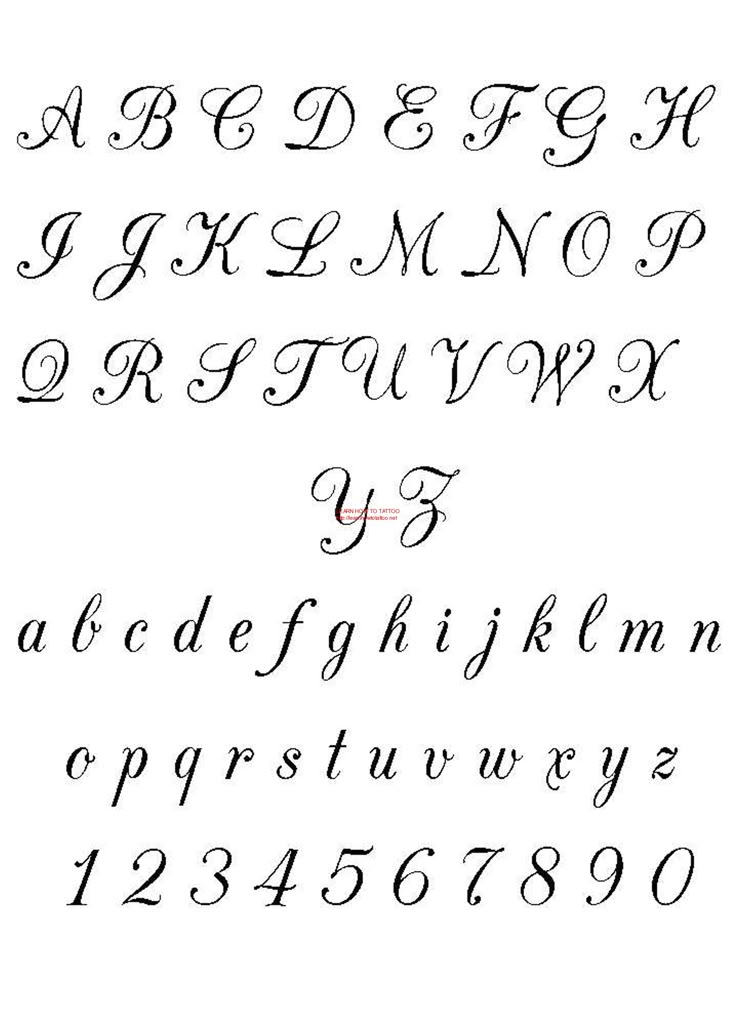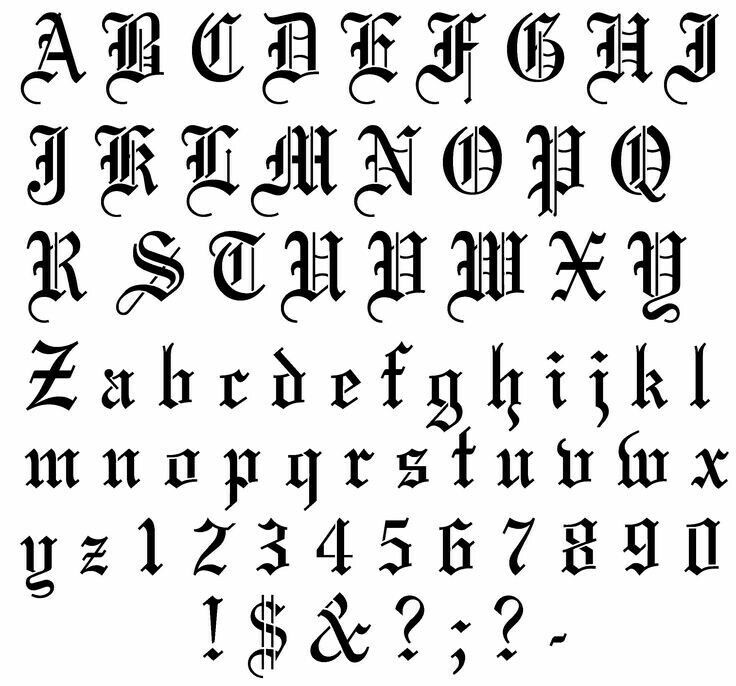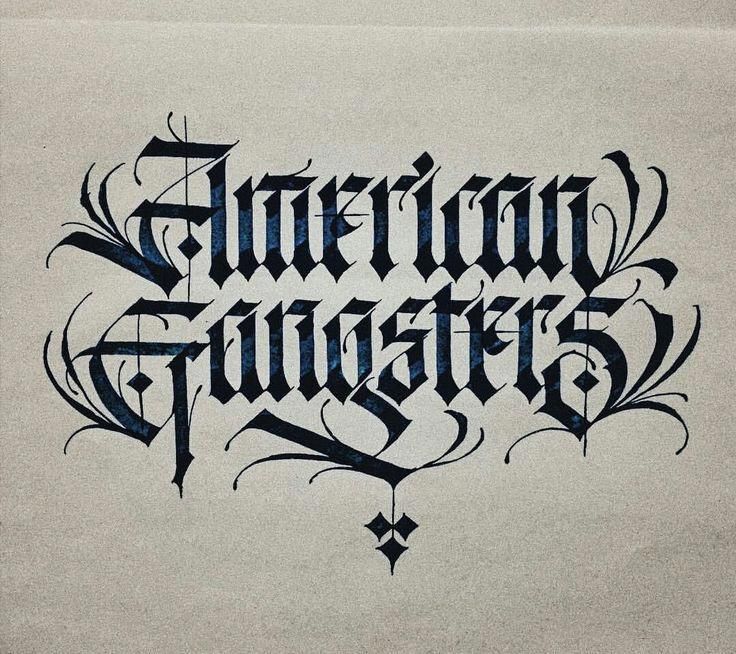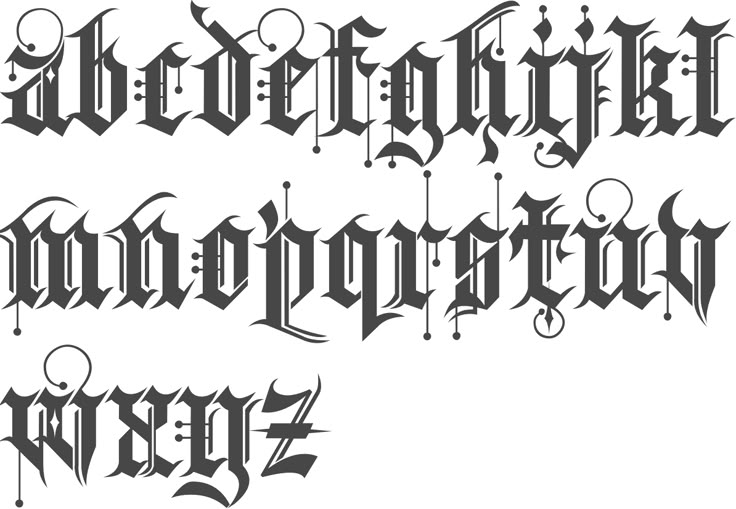
Письма для татуировок, откройте для себя лучшие шрифты
При выборе дизайна, в котором есть буквы для Татуировки Было бы неплохо черпать вдохновение в нескольких шрифтах. Часто зависит от того, что мы собираемся написать, чтобы решить, какой шрифт нам подойдет лучше всего.
Таким образом, В этой статье мы подготовили множество шрифтов, чтобы вы могли выбрать тот, который вам больше всего нравится.Кроме того, они разделены в зависимости от того, как они лучше всего подходят для одного слова или фразы.
Типографика, тысяча шрифтов для одного сообщения
Человек, как и положено одной из его главных характеристик – творчеству, изобретает шрифты с тех пор, как научился писать. С изобретением печатного станка количество букв увеличилось, а с изобретением компьютеров даже больше.
В этой статье мы не будем ограничиваться классическим разделением типографики, часто определяемым в зависимости от времени, в которое они были изобретены (например, готики, имитирующие письменность средневековья, были одними из первых, кто появился) , но мы сделаем два деления. Эти два подразделения ищут утешения, когда дело доходит до вдохновитесь вашим следующим дизайном, состоит ли он из слова или целой фразы (Хотя, как всегда, подразделения только пытаются вам помочь, вы можете пропустить их как хотите, ведь это же ваша татуировка!).
Шрифты из одного слова
Шрифты, которые мы представляем ниже, идеально подходят для использования в качестве букв для татуировок, которые состоят из одного слова, максимум двух или трех.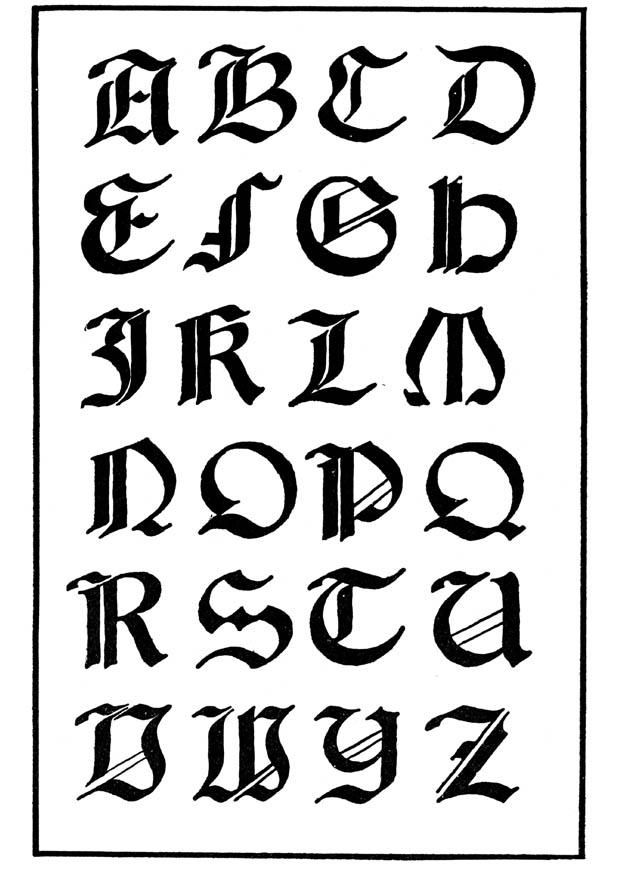
Они идеально подходят для ношения в больших местах, например, на руках, ногах, спине или груди. Имейте в виду, что татуировщик попросит вас выбрать большое пятно, потому что со временем татуировка расширяется, и буквы могут сойтись вместе, что не очень эстетично.
готика
Один из самых известных шрифтов – Gothic, который, как мы уже сказали, стремится имитировать стиль средневековых текстов. Его замысловатые штрихи и оформление в черном цвете делают его довольно эффектным шрифтом (который также сложно замаскировать в будущем).
Цирк
Очень яркий стиль, который вы также можете комбинировать с другими цветами (красный, синий, желтый …), – это шрифт, имитирующий стиль цирка. Подобно традиционному, хотя и не полностью, буквы могут сопровождать дизайн в соответствии с этим шрифтом.
Tradicional
Конечно, когда мы думаем о буквах для тату, первое, что приходит на ум, – это шрифт этого типа. Несколько тоньше, чем предыдущие, ему удается выделяться как своей формой, так и оттенком цвета, который он может придавать своим буквам.
Grafiti
Татуировка, имитирующая граффити, также идеально подходит для вдохновения из татуировки из одного слова, которая должна быть очень драматичной. Черно-белый или цветной, украшенный рисунками или просто буквами, это очень мощный городской стиль.
С рисунками внутри
Наконец, стиль полностью соответствует рок-пластинкам, требующий грандиозного дизайна с гигантскими текстами: Речь идет об украшении внутренней части букв рисунком, который вам больше всего нравится (но, конечно, согласно тому, что на нем написано). Окончательный, хорошо сделанный, потрясающий дизайн.
Шрифты для фразы
Шрифты для более чем одного слова отличаются более тонким шрифтом, чем предыдущие.
В большинстве случаев они имитируют человеческую каллиграфию, что делает их идеальными для дизайна с фразой, которую вы хотите легко и чисто прочитать.
Место, где можно будет нанести эти татуировки, будет зависеть от того, сколько это будет длиться. Если это очень короткая фраза, небольшие участки, такие как запястье, предплечье, пальцы, локоть, колено или шея, идеальны. Для более длинных предложений или более крупных дизайнов рекомендуется выбирать более крупное место, такое как бок, бицепсы, грудь …
Написано от руки
Используя шрифт, имитирующий рукописный стиль, вы получите очень естественный и сдержанный дизайн. Кроме того, есть сотни букв, из которых можно почерпнуть вдохновение, поскольку у всех нас разные буквы. На самом деле, хорошая идея сделать татуировку более индивидуальной – вдохновиться почерком любимого человека.
Машинописный
Теперь, когда все пишется на компьютере, выбор шрифта, имитирующего машинную запись, – довольно ностальгический вариант, особенно для тех из нас, кто научился писать с их помощью. Выбирайте такой шрифт для дизайна, который навевает воспоминания или, например, изобразит фрагмент книги.
Украшение Feathergraphy
Дизайн: Måns Grebäck
Шрифт Argel
Дизайн: Billy Argel
HIGH ON FIRE
Дизайн: Billy Argel
5 Другие алфавиты
Шрифты могут различаться как нюансами стиля, так и особым написанием.